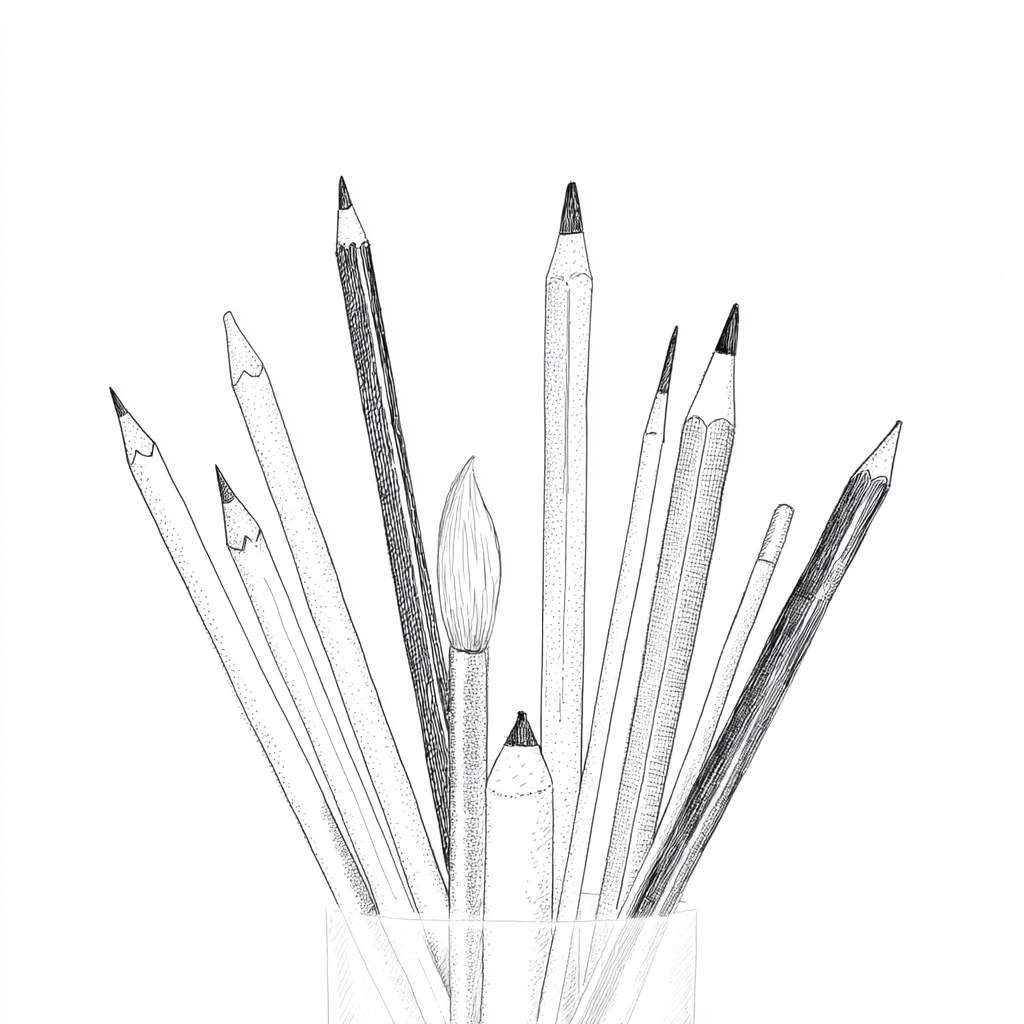
캘리그라피라고 하면 붓이나 펜을 떠올리기 쉬운데요, 사실 연필만으로도 충분히 아름다운 글씨를 그릴 수 있어요. 연필 캘리그라피는 단순히 글씨를 쓰는 걸 넘어, 섬세한 표현과 감성을 담아내는 창작 활동이에요.
특히 초보자에게 연필은 가장 친숙하면서도 접근하기 쉬운 도구라, 입문용으로 딱 좋아요. 굳이 고급 장비나 비싼 도구가 없어도 손에 익은 연필 하나면 감성적인 글씨를 시작할 수 있답니다.
이번 글에서는 연필로 시작하는 캘리그라피에 필요한 준비물을 꼼꼼하게 알려줄게요. 직접 써보고 괜찮았던 도구들도 함께 소개하니까 캘리 입문에 많은 도움이 될 거예요.
지금부터 하나하나 알아보면서, 연필 캘리그라피의 매력을 제대로 느껴볼까요? 그럼 시작해요! ✏
✏ 연필 캘리그라피란?
연필 캘리그라피는 연필을 이용해 감성적인 손글씨를 쓰는 예술 활동이에요. 기존의 붓글씨나 펜글씨와 달리, 부드럽고 따뜻한 느낌을 연출할 수 있어 인기가 많아요. 무엇보다 쉽게 구할 수 있는 연필 하나만 있으면 시작할 수 있다는 게 큰 장점이에요.
연필 특유의 농도 조절이 가능하다는 점도 매력 포인트예요. 힘을 주어 눌러 쓰면 진하고 굵은 선이, 가볍게 쓰면 부드럽고 여린 선이 나오기 때문에 감정 표현이 섬세하게 드러나요. 이런 부분이 감성적인 문장이나 짧은 시를 담을 때 큰 장점이 되죠.
특히나 연필은 실수해도 쉽게 지울 수 있어서 초보자도 부담 없이 시작할 수 있어요. 연필심이 부러지거나 번질 걱정도 없고, 손에 익숙한 도구라서 캘리그라피 입문자에게 부담 없는 선택이랍니다.
‘내 글씨는 못생겨서 캘리그라피 못 해…’라고 생각했다면 더더욱 연필부터 시작해보는 걸 추천해요. 나도 처음엔 글씨가 삐뚤빼뚤했는데, 연필로 천천히 연습하다 보니 어느 순간 나만의 감성이 담긴 글씨가 나오더라고요. 이게 내가 생각했을 때 연필 캘리그라피의 가장 큰 매력이에요.
📝 연필 캘리그라피 특징 비교표
특징 장점 단점 심의 농도 조절 감정 표현에 유리 지속적인 연습 필요 수정 가능 지우개로 쉽게 정리 가능 자주 지우면 번짐 발생 도구 접근성 저렴하고 누구나 소지 전문적인 느낌은 부족할 수 있음 연필 하나로 시작하는 캘리그라피는 단순한 도구 이상의 의미를 가질 수 있어요. 손에 익은 필기감과 부드러운 선의 흐름이 주는 안정감은 다른 도구들과는 또 다른 감성을 전달해준답니다. ✨
🛠 캘리그라피 필수 준비물
연필 캘리그라피를 제대로 즐기기 위해서는 몇 가지 기본 준비물이 필요해요. 특별히 고가의 장비는 없지만, 글씨의 질을 높이고 연습의 효율을 높여주는 도구들이 몇 가지 있어요. 이 준비물만 갖추면 본격적으로 감성 글씨를 시작할 수 있답니다.
가장 먼저 필요한 건 연필이에요. HB부터 6B까지 다양한 연필 중에서 농도를 조절할 수 있는 몇 가지를 함께 구비해두면 좋아요. 그리고 고무 지우개나 지우개펜 같은 도구도 정교한 수정에 유용하답니다.
또 하나 중요한 건 종이에요. 매끄러운 일반 A4용지는 번지지 않아 초보자에게 적합하고, 스케치북이나 캘리그라피 전용 노트를 사용하면 결과물의 완성도를 높일 수 있어요. 너무 두꺼운 종이는 연필 자국이 잘 나지 않을 수 있어요.
연필깎이나 샤프너도 중요해요. 일정한 두께와 뾰족한 심을 유지해야 예쁜 글씨를 쓸 수 있으니까요. 손에 잘 맞는 필기 보조도구(예: 연필 그립)도 함께 사용하면 손의 피로를 줄일 수 있어요.
🧰 연필 캘리그라피 준비물 정리표
준비물 용도 추천 여부 HB~4B 연필 선 굵기, 농도 조절 👍 필수 지우개/지우개펜 정밀 수정 👍 필수 스케치북 연습 및 보관 👍 적극 권장 연필깎이 심 유지 👍 필수 연필 그립 손목 피로 방지 👌 선택 이 도구들만 있으면 부담 없이 연필 캘리그라피를 시작할 수 있어요. 가장 중요한 건 꾸준히 연습하며 자신만의 스타일을 만들어 가는 거예요. 필수 도구를 잘 갖추고 나면, 이제 어떤 연필을 고르면 좋을지 알아봐야겠죠?
✍ 연필 선택 팁과 추천
연필이라고 다 같은 연필이 아니에요. 캘리그라피에 적합한 연필을 고르려면, 심의 농도와 재질, 손에 잡히는 그립감까지 고려해야 해요. 각각의 목적에 따라 다양한 연필이 있으니, 글씨 스타일에 맞는 연필을 선택하는 게 중요해요.
가장 기본적으로는 HB 연필을 많이 사용해요. 중간 농도의 심이라 연습용으로 적합하거든요. 조금 더 진한 표현을 원하면 2B, 4B, 6B 같은 부드러운 연필을 쓰면 좋아요. 특히 4B 이상은 농도가 진하고 부드러워 선이 자연스럽게 흐르기 때문에 감성적인 느낌을 살릴 수 있어요.
샤프를 사용할 수도 있지만, 일반 연필이 손의 압력과 흐름을 더 잘 표현해주기 때문에 처음에는 일반 연필을 추천해요. 연필을 깎는 것도 작은 준비과정의 일환이라, 감성을 느낄 수 있는 부분이기도 해요.
그리고 브랜드마다 심의 느낌도 다르기 때문에, 몇 가지 연필을 직접 써보고 자신에게 맞는 것을 찾는 것도 좋아요. 트래디셔널한 스타일을 원한다면 톰보우(Tombow)나 미쓰비시(Mitsubishi) 연필이 많이 추천돼요.
📄 종이와 스케치북 고르기
좋은 연필이 있어도 종이가 따라주지 않으면 원하는 느낌을 내기 힘들어요. 종이는 연필의 필압을 그대로 받는 재료이기 때문에, 표면 질감과 두께, 색상이 결과물에 큰 영향을 줘요.
연습용으로는 일반 복사지나 무지 노트로도 충분해요. 하지만 작품을 만들거나 기록용으로 남기고 싶다면 캘리그라피용 노트나 스케치북이 좋아요. 너무 거친 질감보다는 부드럽고 살짝 코팅된 종이가 선명한 필체를 살릴 수 있답니다.
특히 미술용 스케치북 중에서는 연필용으로 적합한 종이들이 많아요. 예를 들면, 120g 이상 중량의 종이는 너무 얇지도 않고 지울 때도 찢어지지 않아 안정적이에요. 색감이 살짝 아이보리 톤이면 눈도 편하고 분위기도 훨씬 좋아 보이죠.
사각사각한 연필 소리와 함께 연습하는 감성, 종이 선택이 반은 좌우한다고 해도 과언이 아니에요. 연습 후 보관을 고려한다면 바인딩이 편한 스프링 노트나 분리형 스케치북도 추천해요.
🧽 지우개와 보조도구 활용법
연필로 작업하다 보면 실수는 필연이에요. 그래서 지우개는 연필 캘리그라피에서 빠질 수 없는 필수 도구 중 하나예요. 단순히 글씨를 지우는 기능을 넘어, 그림자나 하이라이트를 표현하는 데도 쓰일 수 있어요.
고무 지우개는 부드럽고 잔흔이 적어 많이 사용돼요. 특히 미술용 지우개는 더 정교하게 표현할 수 있어서 유용해요. 또, 펜처럼 생긴 지우개펜도 있어요. 아주 좁은 부분이나 선 끝을 살짝 정리할 때 딱이에요.
또 하나 유용한 보조도구는 ‘문지르개’ 또는 블렌더 도구예요. 연필의 선을 문질러 자연스럽게 이어주는 역할을 해요. 섀딩이나 배경 표현할 때 특히 유용해서, 글자 주변을 부드럽게 강조할 때 많이 활용해요.
마지막으로 작업 후에는 고무 찌꺼기를 잘 털어내는 브러시도 있으면 좋아요. 손으로 쓸면 번지거나 기름이 묻을 수 있으니까, 작은 붓으로 살살 털어내는 게 깔끔한 작품을 유지하는 팁이에요.
💡 연습을 위한 팁과 꿀정보
연필 캘리그라피는 꾸준한 연습이 가장 중요해요. 특별한 재능이 없어도, 매일 짧은 시간이라도 꾸준히 쓰면 실력이 금방 늘어요. 먼저 하루 한 문장 쓰기부터 시작해보세요. 좋아하는 명언이나 가사 한 줄을 매일 써보는 것도 좋아요.
글씨체를 연습할 때는 따라 쓰기를 추천해요. SNS나 책에서 마음에 드는 글씨를 따라 쓰며, 손의 흐름을 익히는 거예요. 무작정 쓰는 것보다는 눈과 손이 함께 기억하게 돼서 효과가 커요.
그림자 효과나 농도 조절은 조금 익숙해졌을 때 도전해도 늦지 않아요. 처음부터 복잡하게 하려고 하지 말고, 선의 흐름과 자간, 행간 등을 익히는 데 집중하는 게 좋아요.
연습한 결과물을 보관해두면 발전 과정이 보이기 때문에, 스스로 동기부여가 되기도 해요. 정리된 노트에 날짜를 적어두면, 나중에 ‘내가 이렇게 글씨를 잘 쓰게 됐구나!’ 하고 뿌듯할 거예요. 🥰
❓FAQ
Q1. 연필 캘리그라피는 어느 정도 연습해야 잘 할 수 있나요?
A1. 하루 10~15분씩 꾸준히 2~3주만 해도 눈에 띄게 좋아져요. 중요한 건 매일 쓰는 습관이에요.
Q2. 연필 캘리그라피와 붓펜 캘리그라피 중에 뭐가 쉬운가요?
A2. 연필이 훨씬 쉬워요! 수정도 쉽고 손에 익숙하니까 처음 배우기엔 연필이 좋아요.
Q3. 샤프 연필로도 가능한가요?
A3. 가능은 하지만 선이 너무 얇고 일정해서 감성 표현엔 다소 부족할 수 있어요.
Q4. 어떤 종이가 제일 좋아요?
A4보다 약간 두껍고 부드러운 스케치북이나 노트가 적당해요. 코팅된 종이도 좋아요.
Q5. 완성작을 보관하려면 어떻게 해야 하나요?
A5. 파일철이나 전용 클리어 폴더에 넣어두면 오랫동안 보관할 수 있어요.
Q6. 손글씨 교본이 따로 있을까요?
A6. ‘감성 손글씨’, ‘캘리그라피 따라쓰기’ 같은 책들이 많이 나와 있어요. 초보자용으로 좋아요.
Q7. 연필심이 자주 부러지면 어떻게 하나요?
A7. 너무 뾰족하게 깎지 않거나, 부드러운 필압으로 쓰면 심이 덜 부러져요.
Q8. 연필 외에 추천 도구가 있을까요?
A8. 연필 그립, 지우개펜, 소형 브러시, 그리고 그림자 표현용 블렌더가 있으면 더 좋아요!